- 마초의 사춘기 기업 철학 담은 전용 폰트 2종 공동 개발
- 브랜드 정체성을 폰트로 구현… 중소기업도 보유 가능한 브랜드 IP 사례
- 윤디자인, 전용 폰트 통한 브랜드 자산화 및 경쟁력 강화 지원 확대
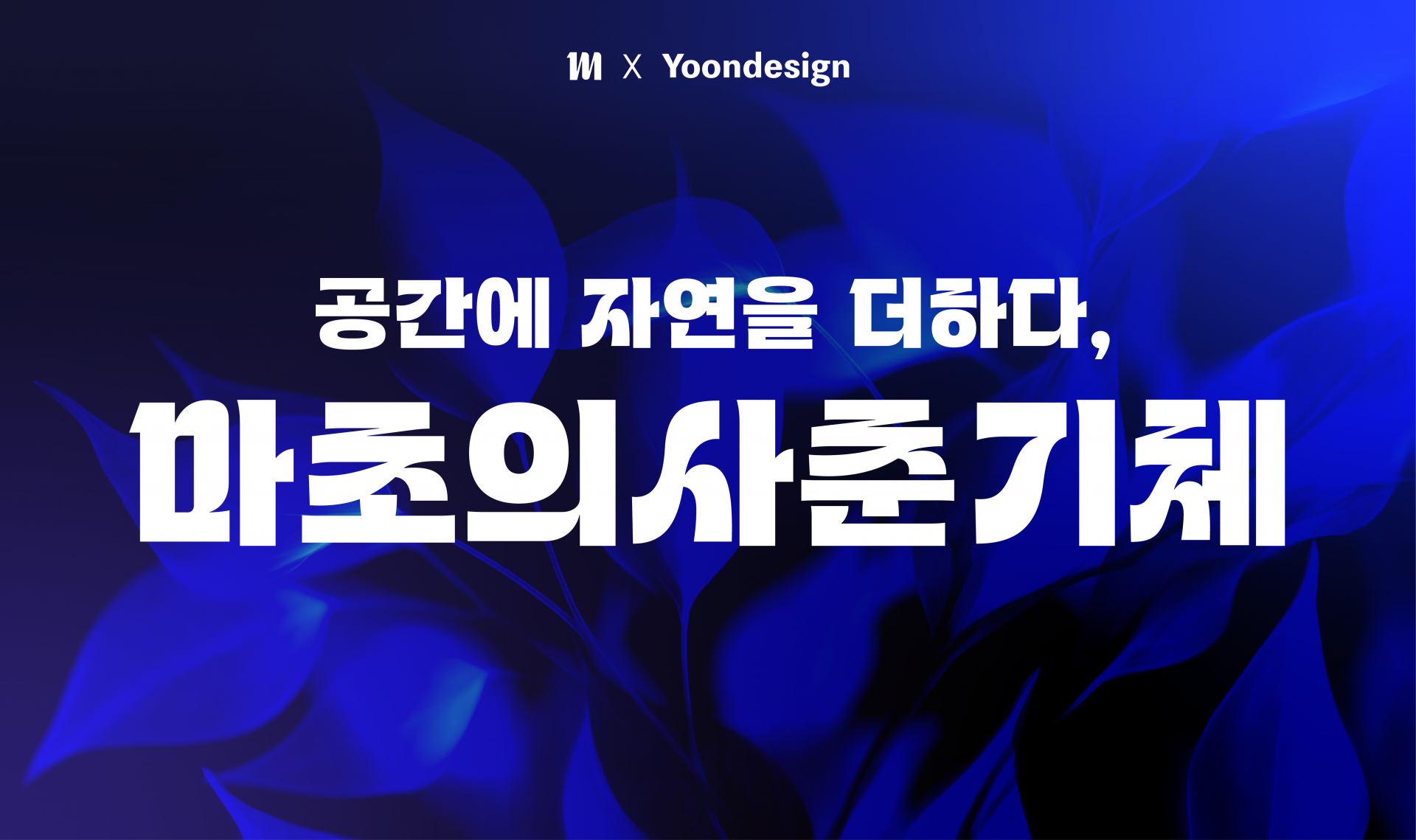
타이포그래피 전문 기업 ㈜윤디자인(대표 윤영호, 조성민)이 바이오필릭 공간 디자인 스튜디오 마초의사춘기(대표 김광수)와 함께 기업 전용 폰트 ‘마초의사춘기체’와 ‘마초의일상체’를 공동 개발했다고 밝혔다.
이번 프로젝트는 중소기업이 브랜드 정체성을 강화하고 기업만의 차별화된 브랜드 자산을 구축할 수 있도록 지원한 사례로, 양사의 철학과 전문성을 결합한 상생형 협업 모델이라는 점에서 의미를 갖는다.
최근 기업 경쟁력은 제품과 서비스의 품질을 넘어 고객이 경험하는 브랜드 전반으로 확장되고 있다. 이에 따라 브랜드의 철학과 정체성을 일관되게 전달하는 전용 폰트는 기업의 핵심 지식재산(IP)이자 장기적으로 축적되는 브랜드 자산으로 주목받고 있다.
특히 기업 전용 폰트는 로고와 슬로건을 넘어 기업의 가치와 메시지를 일관된 시각 경험으로 연결하는 타이포 브랜딩 전략의 핵심 요소로 평가받는다.
윤디자인은 이번 프로젝트를 통해 마초의사춘기가 추구하는 공간 철학과 브랜드 정체성을 폰트에 담아 기업 가치를 효과적으로 전달할 수 있도록 했다.
이를 통해 마초의사춘기는 기업의 철학과 개성을 반영한 전용 폰트를 브랜드 자산으로 확보하고, 온,오프라인 고객 접점 전반에서 일관된 브랜드 경험을 제공할 수 있는 기반을 마련했다.
이번에 개발된 ‘마초의사춘기체’와 ‘마초의일상체’는 마초의사춘기가 추구하는 자연 친화적 공간 철학과 브랜드 정체성을 담아낸 결과물이다.
헤드라인용 ‘마초의사춘기체’는 브랜드 로고의 단단한 세리프 구조를 계승해 강인한 생명력과 존재감을 표현했으며, 본문용 ‘마초의일상체’는 부드러운 곡선과 안정적인 구조를 통해 자연스러운 가독성과 친근한 인상을 구현했다.
윤디자인은 폰트 개발 과정에서 마초의사춘기가 지닌 ‘강인함’과 ‘유연한 감수성’이라는 상반된 특성을 식물의 생명력과 유기적인 형태로 해석해 디자인에 반영했다.
윤디자인 관계자는 “기업 전용 폰트는 단순한 디자인 요소를 넘어 기업만의 철학과 정체성을 담아내는 중요한 자산”이라며 “이번 협업은 중소기업도 전용 폰트를 통해 브랜드 IP를 구축하고 차별화된 경험을 제공할 수 있다는 가능성을 보여준 사례로, 앞으로도 다양한 기업과 협력해 브랜드 자산화와 경쟁력 강화를 위한 타이포 브랜딩 프로젝트를 지속 확대해 나갈 계획”이라고 밝혔다.